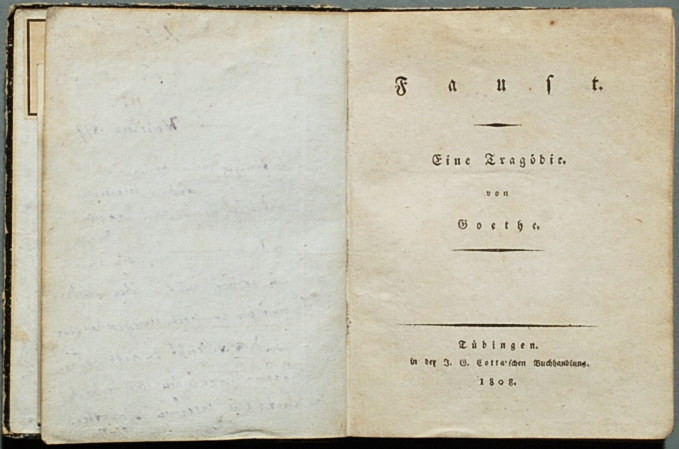
Zwangsverbünde im gesperrten Fraktursatz: Das ſt
Daß die Zwangsverbünde immer zu setzen sind sollte in jedem herkömmlichen Typographiebuch stehen. In Marahrens’ Vollständigem theoretisch-praktischen Handbuch der Typographie steht beispielsweise gleich am Anfang des Kapitels Die Ligaturen (Hervorhebung von mir):
Es giebt in der Fraktur, soweit dieselbe zur deutschen Sprache benutzt wird, zweierlei zusammengegossene Buchstaben, nämlich solche, von denen die Sprache selbst, die Orthographie, eine Verbindung zweier erfordert, als ch, ck, ß, tz, und dann solche, welche im Interesse der typographischen Schönheit und Nützlichkeit verbunden sind: ??, ?i, ll, fl, fi und ?t.
Diese Information ist falsch, denn die Ligatur ‹?t› gehört doch auch zu den obligatorischen Ligaturen! Die obligatorischen Ligaturen im Fraktursatz sind ‹ch›, ‹ck›, ‹?t› und ‹tz› (von mir aus auch noch ‹ß›, wenn man es denn unbedingt als Ligatur betrachten will, und nicht als eigenen Buchstaben).
In Bezug auf das ‹?t› herrscht jedoch Unsicherheit. Mein Verdacht ist, dafür sei der Duden verantwortlich. In der aktuellen Ausgabe wird das ‹?t› überhaupt nicht genannt, sondern nur ‹ch›, ‹ck› und ‹tz›.
Ferner bin ich schon der Behauptung begegnet, dass das ‹?t› in gesperrtem Fraktursatz zwar getrennt werde, aber nicht gesperrt. Gemäss Diskussion:Sperrsatz – Wikipedia#Was ist mit dem ?t? stehe das so im Leipziger Duden von 1968. Das mag dort vielleicht wirklich stehen – in sämtlichen Beispielen von gesperrtem Fraktursatz, die ich bislang gefunden habe, wird aber für das ‹?t› im Sperrsatz genau dieselbe Glyphe verwendet wie im normalen, nicht-gesperrten Satz (konsultiert habe ich ein gutes Dutzend Bücher aus dem 19. Jahrhundert, die über Googles Erweiterte Buchsuche in vollständiger Ansicht verfügbar waren). Ich halte also diese Behauptung für nicht besonders glaubwürdig.
Meine (völlig unbelegte) Vermutung ist die: Irgendwann einmal hat sich die merkwürdige Behauptung in den Duden eingeschlichen, dass das ‹?t› im gesperrten Fraktursatz zwar getrennt werde, aber nicht gesperrt. Weil diese Behauptung derart merkwürdig ist, hat man in späteren Duden-Auflagen das ‹?t› ganz einfach unterschlagen.
Weiss vielleicht hier jemand Genaueres dazu? Meine wenigen schlauen Typographie-Bücher schweigen dazu leider.
Hans-Georg schreibt hierzu in seinem Frakturaufsatz auf S. 18:
[…]
Im Sperr?atz werden die Ligaturen, (außer den Zwangsligaturen) in Einzelbuch?taben aufgelö?t und ge?perrt. „?t“ wird zwar ebenfalls aufgelö?t, jedoch nicht ge?perrt; gleiches gilt für die Verbindung „?s“ in der neuen Recht?chreibung. […]
Dies ist die einzige Seite, wo ich außer im bekannten Leipziger Duden noch etwas dazu finde, weder der Frakturknigge von Delbanco, noch das Hinweisdokument von Helzel schreiben etwas dazu und bei der Wikipedia steht mal wieder ganz falsch, dass ?t eine Zwangsligatur sei, gleich mal streichen, denn diese Information finde ich nirgendwo.
Ich denke, es stimmt schon, dass das ‹?t› ebenfalls zu den obligatorischen Ligaturen gehört. Warum würde es sonst in allen alten Druckwerken, die ich bislang gefunden habe, übereinstimmend wie eine obligatorische Ligatur behandelt? Ich glaube nicht, dass das ein Zufall ist.
Hier mal ein ganz schnelles Gegenbeispiel:
Da steht doch eindeutig „F a u ? t“ und nicht „F a u ?t“.
Vielleicht gab es auch Unheitlichkeiten, in den Satzregeln betreffs „?t“ im 19. Jh., denn ich habe wie du auch ein Beispiel mit ungetrennter Ligatur gefunden. Es könnte ja sein, dass die Dudenregel sozusagen am Ende der Kompromiss zwischen dem Trennen der Ligatur und einer Zwangsligatur war.
Eine Google-Buchsuche nach intitle:faust ergibt Dutzende von Resultaten, die allermeisten mit ‹?t›-Ligatur, daneben einige mit ‹st› im Titel. Das gesperrte ‹? t›, auf das du verwiesen hast, würde ich jetzt mal auf Anhieb zusammen mit den verschiedenen Beispielen von ‹st› in eine Abweichler-Gruppe einordnen, während in der Mehrheit der Fälle das ‹?t› als obligatorische Ligatur auftritt.
Ich würde einfach gerne mal wenigstens ein einziges Beispiel für ein Druckwerk sehen, das die Regel aus dem Leipziger Duden von 1968 illustriert. Wenigstens ein einziges sollte doch auffindbar sein!
Der Aufsatz von Hans-Georg Soldat scheint mir keine besonders zuverlässige Quelle zu sein. Dort steht, in Antiqua würden «im allgemeinen nur sog. ästhetische Ligaturen» verwendet, während die «„morphemischen Ligaturen“» geradezu ein Merkmal der Fraktur seien. Das stimmt selbstverständlich nicht.
Also ich habe gelernt, daß im gesperrten Satz Ligaturen grundsätzlich nicht zu setzen sind.
Das würde sich ja auch irgendwie widersprechen... :?
Auch bei den Ligaturen „ch“, „ck“ und „tz“ im Fraktursatz?
Ich bin mir nicht sicher, ob das explicit so gesagt wurde; es war halt eine allgemeine Satzregel, die ja auch sinnvoll ist. Stell Dir mal oben die Zeile » F a u ? t « mit Ligatur vor — sieht immer fürchterlich aus.
Man findet kaum einheitliche Richtlinien in den verschiedenen Fachbüchern. Im satztechnischen Fachlexikon (Wien 1925) steht dazu:
Aber es gab doch sehr wohl Regeln. Und klar, im frühen 19. Jahrhundert war die Einheitlichkeit noch lange nicht so gross. Im späten 19. Jahrhundert und im frühen 20. Jahrhundert werden aber sehr wohl einheitliche Regeln bestanden haben – und mir scheint, die «zusammengegoogelten Beispiele» zeigen das auch deutlich, denn sie sind weitestgehend einheitlich (Unheinheitlichkeiten beschränken sich auf besonders alte Bücher). Ferner sind Behauptungen wie diejenigen in Niels Satztechnischem Taschen-Lexikon bestimmt nicht aus der Luft gegriffen.